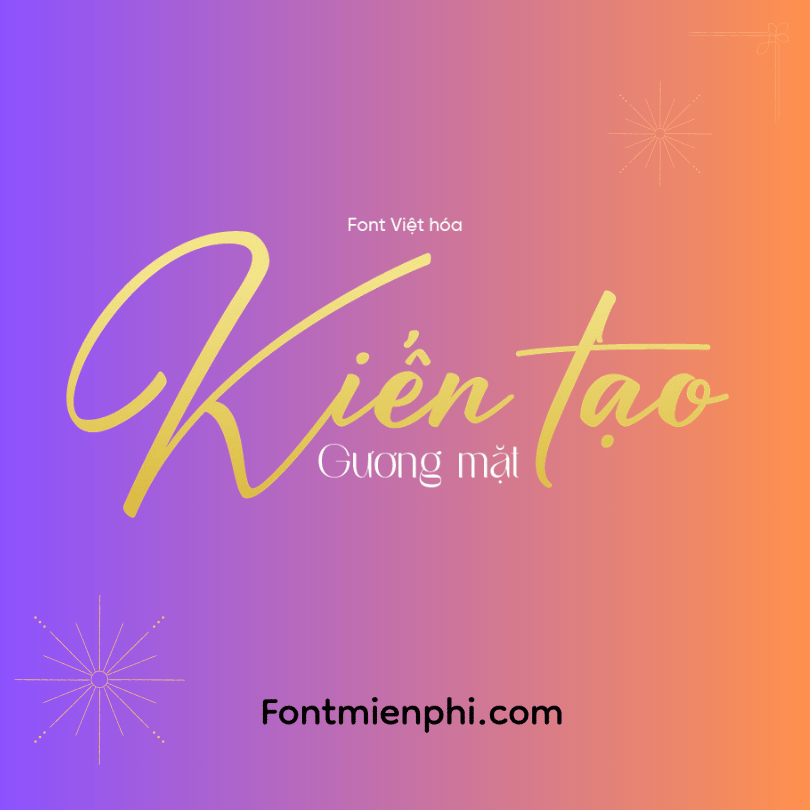
Font Việt hóa 1FTV VIP Madinah Authentic
Font Việt Hóa 1FTV VIP Madinah Authentic – Nét Chữ Ả Rập Đậm Chất Trung Đông
Đặc điểm độc đáo:
• Phong cách chữ Arabic-inspired với đường nét uốn lượn nghệ thuật
• Được Việt hóa hoàn chỉnh, hỗ trợ đầy đủ Tiếng Việt Unicode
• Bao gồm 4 biến thể: Regular, Bold, Outline và Shadow
• Độ phân giải cao, in ấn sắc nét ở mọi kích thước
Ứng dụng đắt giá:
۞ Thiết kế nhận diện thương hiệu Trà – Cà phê Ả Rập
۞ Bao bì sản phẩm hương liệu, mỹ phẩm Oriental
۞ Menu nhà hàng ẩm thực Trung Đông
۞ Background phim ảnh, game phong cách Arabian
۞ Thiệp mời sự kiện đẳng cấp
Pro tips:
✓ Kết hợp với họa tiết Islamic pattern cho thiết kế chuẩn Middle-East
✓ Dùng làm font chính cho các thương hiệu premium